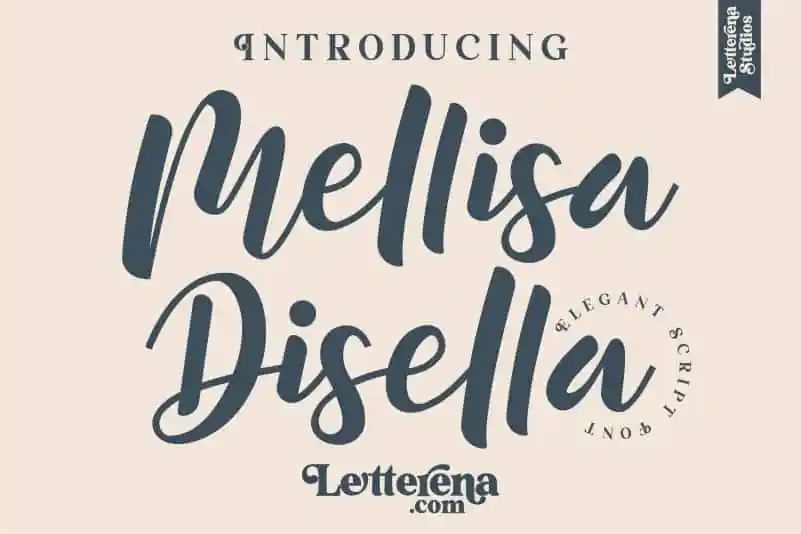
A fonte Mellisa Disella é uma elegante tipografia escrita a mão criada por Letterenastudios, perfeita para qualquer projeto que busque um toque romântico de calligrafia. Convidativa e sofisticada, ela se destaca em aplicações como logos, projetos de marca, designs de móveis de quarto, embalagens de produtos, xícaras, citações, posters, sacolas de loja, camisetas, capas de livro, cartões de nome, convites de aniversário, cartões de presente, etiquetas e até mesmo para água da máquina ou eventos especiais. Com seu traço delicado e elegante, Mellisa Disella se encaixa perfeitamente em qualquer projeto que necessite de uma aparição única e sofisticada. Seja para um design exclusivo ou um produto de alta qualidade, sua beleza simplesmente toma o lugar como a escolha ideal para capturar o resplendor de sua marca.